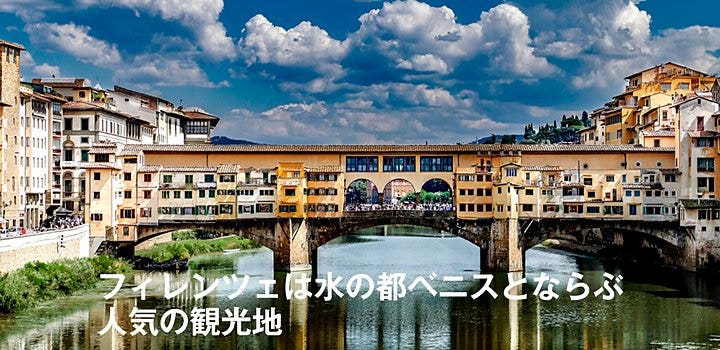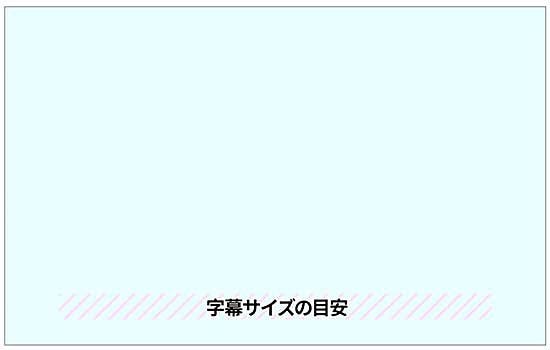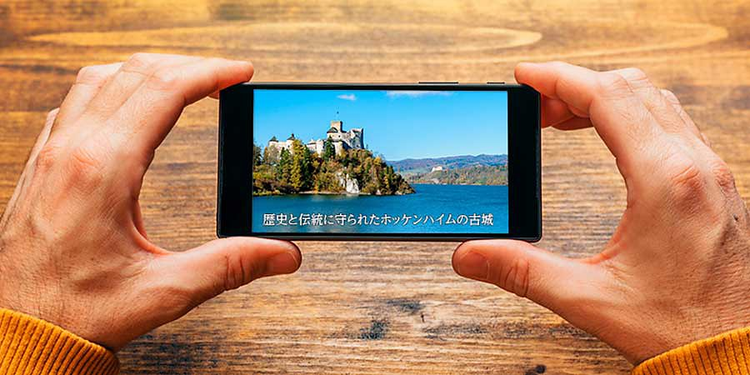
YouTubeや
多くの
動画の内容をわかりやすくする字幕文字
動画に
YouTubeの
いずれに
動画を
ブログなどの
動画は
ある場面では
せっかく
字幕・テロップに最適なフォント選びの基本
字幕に
フォントは
明朝体は
いまでは
ゴシック体は
映像のイメージから書体を選ぶ
動画・映像に
映画の
たとえば、
フォントが
文字を読みやすくするデザイン処理
動画は
コントラストとは
暗い映像に
海や空など
あざやかな
もし、
このほか、
ただし、
字幕作成は視聴サイズを考慮して
動画・映像を
デスクトップパソコンでは
サイズの
特にYouTubeの
字幕の
誰がどのような